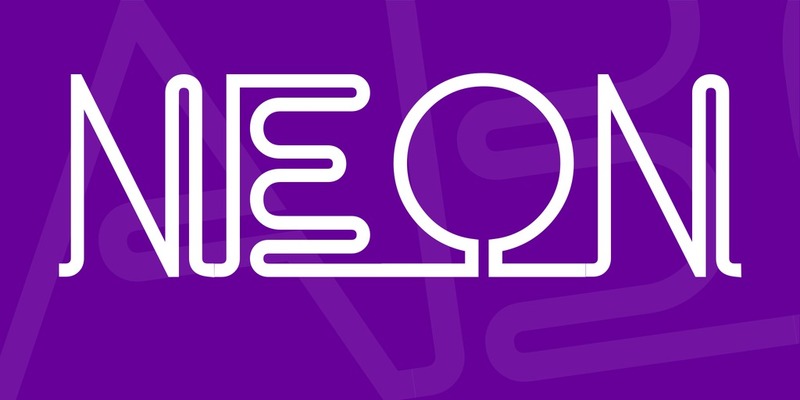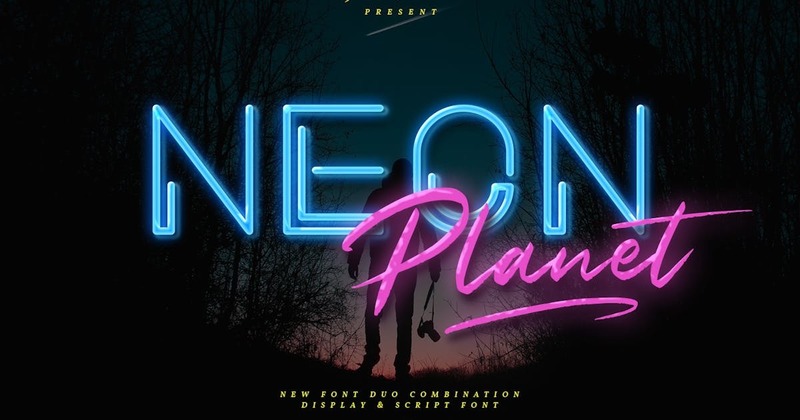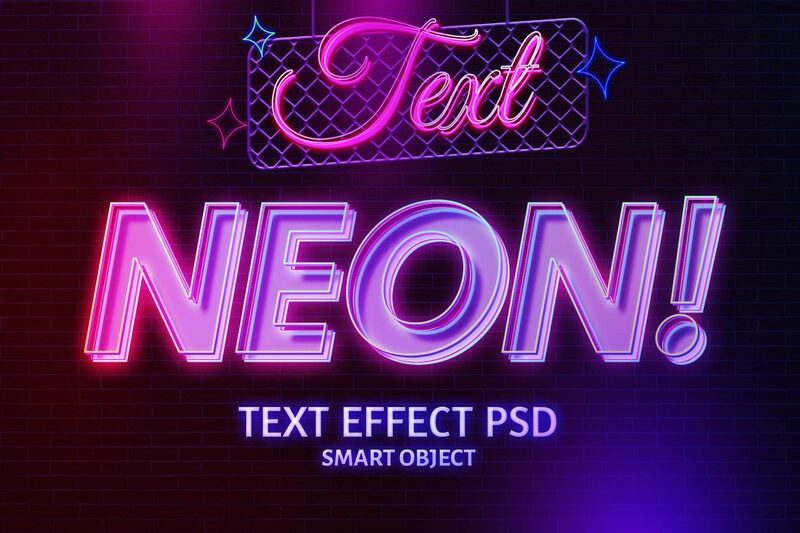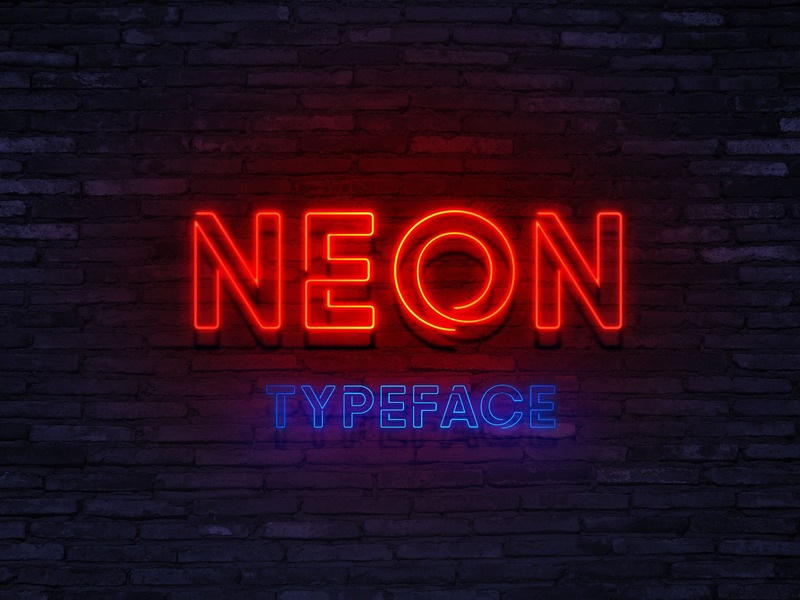
Tổng hợp 12 Font Neon đẹp dành cho thiết kế
Font Neon là nhóm font chữ mô phỏng hiệu ứng đèn neon được sử dụng rộng rãi trong bảng hiệu, quảng cáo và nghệ thuật đường phố từ thế kỷ 20. Với vẻ ngoài nổi bật, ánh sáng ảo diệu và đường nét sắc sảo, font Neon không chỉ truyền tải phong cách retro cổ điển mà còn mang lại cảm giác hiện đại, năng động và phá cách.
Đặc điểm nổi bật của Font Neon
• Đường nét giống đèn ống Neon: Font thường có các nét uốn cong tròn trịa, đều đặn, mô phỏng hiệu ứng ánh sáng từ các ống đèn neon – mang lại cảm giác phát sáng ngay cả khi chỉ sử dụng dưới dạng văn bản.
• Phong cách retro và hiện đại kết hợp: Mặc dù có nguồn gốc từ các biển hiệu cổ điển thập niên 80, nhưng font Neon vẫn được sử dụng nhiều trong thiết kế hiện đại – đặc biệt là các sản phẩm giải trí, âm nhạc, công nghệ, thời trang…
• Hiệu ứng nổi bật khi kết hợp với màu sắc và nền tối: Font Neon phát huy tối đa hiệu quả khi đi kèm hiệu ứng phát sáng, đổ bóng hoặc các phối nền tối – tạo nên sự thu hút cực mạnh.
• Phong phú về biến thể: Hiện nay có rất nhiều biến thể font Neon: từ nét đơn, nét đôi (double-line), có chân, không chân, dạng script uốn lượn đến dạng block vuông vức.
Ứng dụng của Font Neon
Font Neon được sử dụng rộng rãi trong các thiết kế hiện đại nhờ vào khả năng tạo hiệu ứng thị giác mạnh mẽ và cảm giác lôi cuốn, đặc biệt phù hợp với những thiết kế mang phong cách “đêm thành thị”, sôi động, phá cách. Dưới đây là những ứng dụng phổ biến nhất của font chữ này:
Poster âm nhạc, lễ hội, sự kiện đêm:
Font Neon đặc biệt phù hợp cho các poster quảng bá sự kiện như DJ show, nhạc hội, tiệc ngoài trời, đêm countdown… với mục đích thu hút ánh nhìn và thể hiện sự náo nhiệt, rực rỡ của sự kiện.
Logo quán bar, lounge, club, cửa hàng thời trang:
Các địa điểm giải trí về đêm thường sử dụng font Neon cho biển hiệu và logo để gợi cảm giác sôi động, hiện đại và cá tính. Các cửa hàng thời trang mang phong cách cá nhân mạnh mẽ, nổi loạn cũng thường chọn kiểu chữ này để thể hiện bản sắc thương hiệu.
Biển hiệu kỹ thuật số, banner mạng xã hội, giao diện website:
Font Neon rất hiệu quả trong các thiết kế digital như banner quảng cáo trên mạng xã hội, giao diện website, video intro… đặc biệt là khi phối hợp với nền tối và hiệu ứng ánh sáng để tạo điểm nhấn nổi bật.
Ấn phẩm nghệ thuật mang phong cách điện ảnh hoặc cyberpunk:
Với cảm hứng từ điện ảnh retro, cyberpunk, viễn tưởng…, font Neon giúp truyền tải cảm xúc thị giác ấn tượng – thường thấy trong các bìa sách, tạp chí, hoặc poster phim với không khí thành phố về đêm, ánh đèn rực rỡ.
Thiết kế game, ứng dụng giải trí, YouTube thumbnail:
Các nhà phát triển game hoặc nhà sáng tạo nội dung YouTube thường dùng font Neon cho ảnh đại diện (thumbnail) hoặc giao diện để tăng sự thu hút và thể hiện sự sôi động, cá tính của nội dung.
Font Neon không chỉ là kiểu chữ, mà còn là công cụ thể hiện sự cá tính, phá cách và tạo điểm nhấn mạnh mẽ cho bất kỳ thiết kế nào. Dù bạn đang thực hiện một poster âm nhạc, một biển hiệu ảo, hay một ấn phẩm truyền thông số, font Neon sẽ luôn là lựa chọn lý tưởng để thu hút sự chú ý và tạo hiệu ứng thị giác ấn tượng. Hãy thử nghiệm và “thắp sáng” thiết kế của bạn với một font Neon phù hợp!